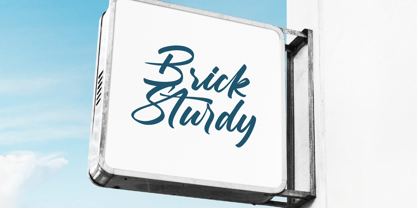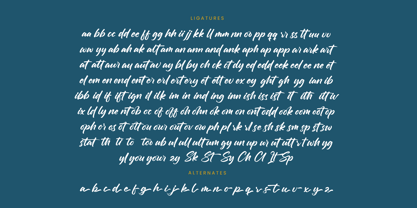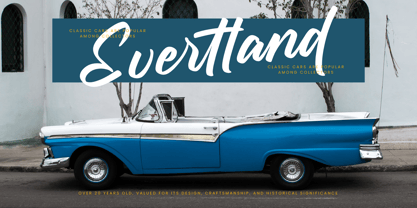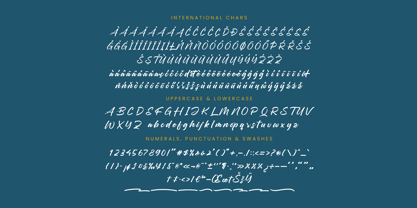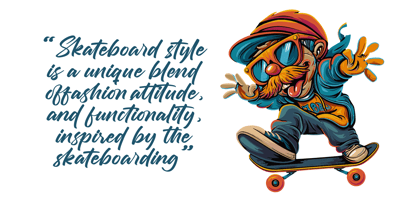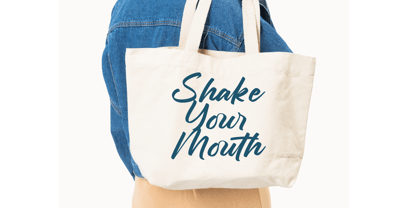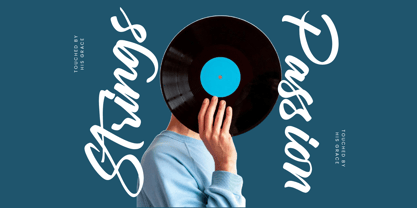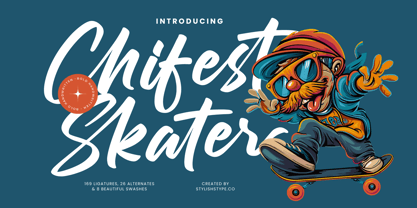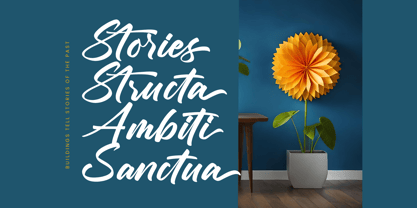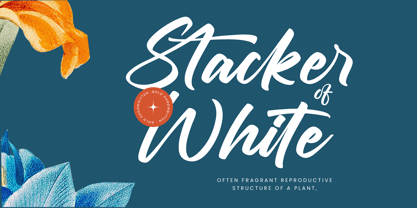
Chifest Skater
La familia tipográfica Chifest Skater fue diseñada por Heru Utama Putra y publicada por Stylishtype Studio. Chifest Skater contiene 2 estilos y opciones de paquete familiar. Más información sobre esta familia
Chifest Skater - Bold Handwritten Font , from Stylishtype, Suitable for any projects such as: logos, branding projects, homeware designs, product packaging, mugs, quotes, posters, shopping bags, t-shirts, book covers, name card, invitation cards, greeting cards, label, photography, watermark, special events, and all your other luxury and beautiful projects that need a Luxury Script taste.